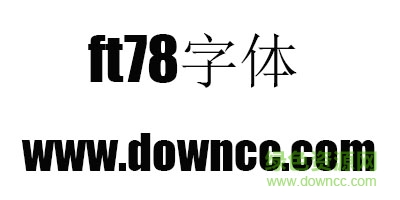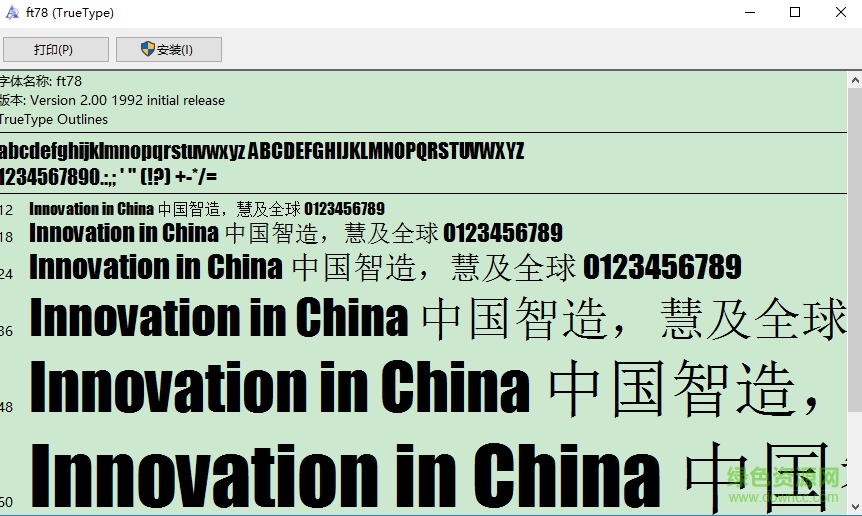
ft78字體是一款非常實(shí)用的英文字體,這款字體結(jié)構(gòu)端正大方,字跡清晰,非常適用于排版印刷、廣告設(shè)計(jì)等領(lǐng)域,需要的朋友歡迎來綠色資源網(wǎng)下載使用!
ft78字體是一款深受用戶喜愛的英文字體,這款字體易讀性強(qiáng),應(yīng)用范圍廣泛,是一款非常不錯(cuò)的英文字體。